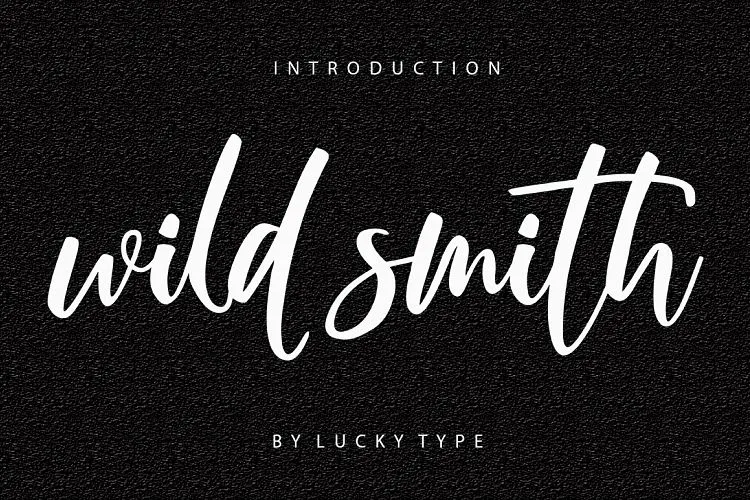
Wild Smith Modern Script Font – Download Grátis
Esta é uma fonte de script esquisito e encantador, projetada para aqueles que buscam algo único no seu trabalho. A Wild Smith Modern Script Font oferece uma experiência visual vibrante, perfeita para quem busca expressar o estilo feminino e trendy em sua arte. Com um design que inclui letras maiúsculas e minúsculas completas, esta fonte pode ser usada de várias maneiras e em diferentes ambientes de projeto. A WildSmith Script é uma nova versão de script moderno com uma base irregular. Ela traz vida e movimento para qualquer trabalho gráfico ou design que você desenvolver, criando um impacto único e atraente. Seja no design de cartões de convite de casamento, cartas de agradecimento, citações, cartazes de bem-vindo, logotipos, cartão de visita ou em qualquer outro projeto onde o uso de texto é crucial, esta fonte oferece uma solução ideal. Suportando alternativas e ligaturas, ela combina perfeitamente com os elementos artísticos que você pode desejar adicionar para dar vida aos seus designs. Também inclui letras iniciais e finais para garantir um acabamento sofisticado. A Wild Smith Modern Script é uma fonte para quem valoriza a expressão autêntica, o design único e a capacidade de transmitir emoção através do texto em um formato visual e criativo. Ideal tanto para trabalhos digitais quanto impressos, este design moderno está pronto para revolucionar suas ideias e torná-las ainda mais memoráveis.